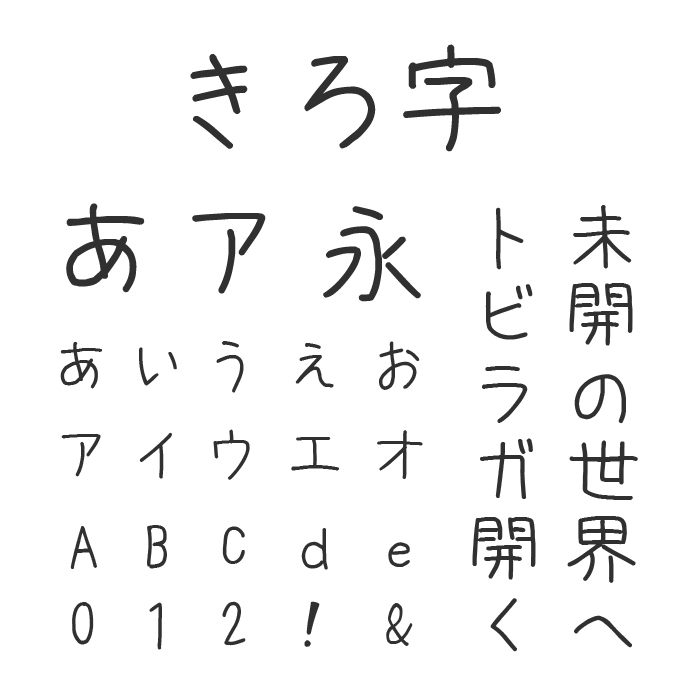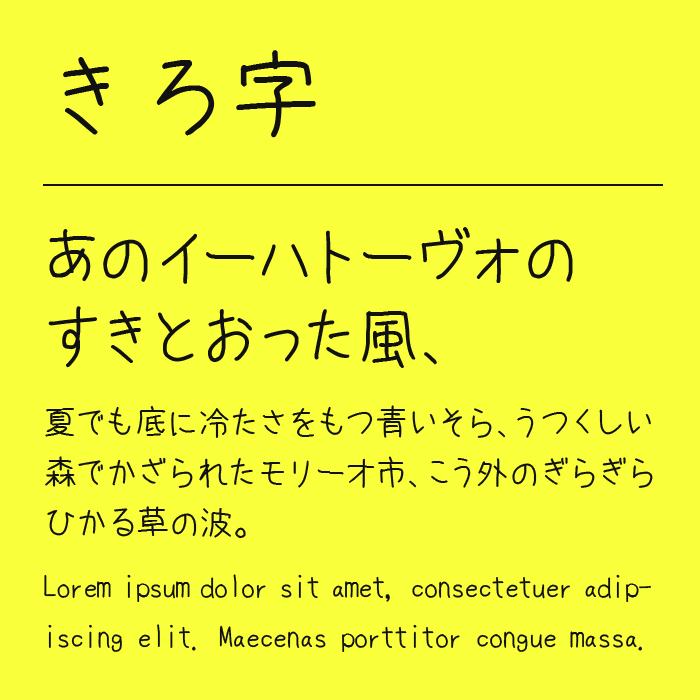
きろ字フォントは、丁寧で均整の取れた文字で、落ち着いた雰囲気の手書きフォントです。
ひらがなの丸みに温かさがあり、読みやすさも損なわれていないバランスのよく可愛らしい文字です。
線の太さは控えめで、空気を含んだようなゆとりを持つフォルムが特徴です。日常的なトーンや、文章量の多いコンテンツでも視線を疲れさせず、自然と読者に寄り添うような使い心地のフォントです。
収録文字は、漢字・ひらがな・カタカナ・アルファベット・数字・記号が収録。